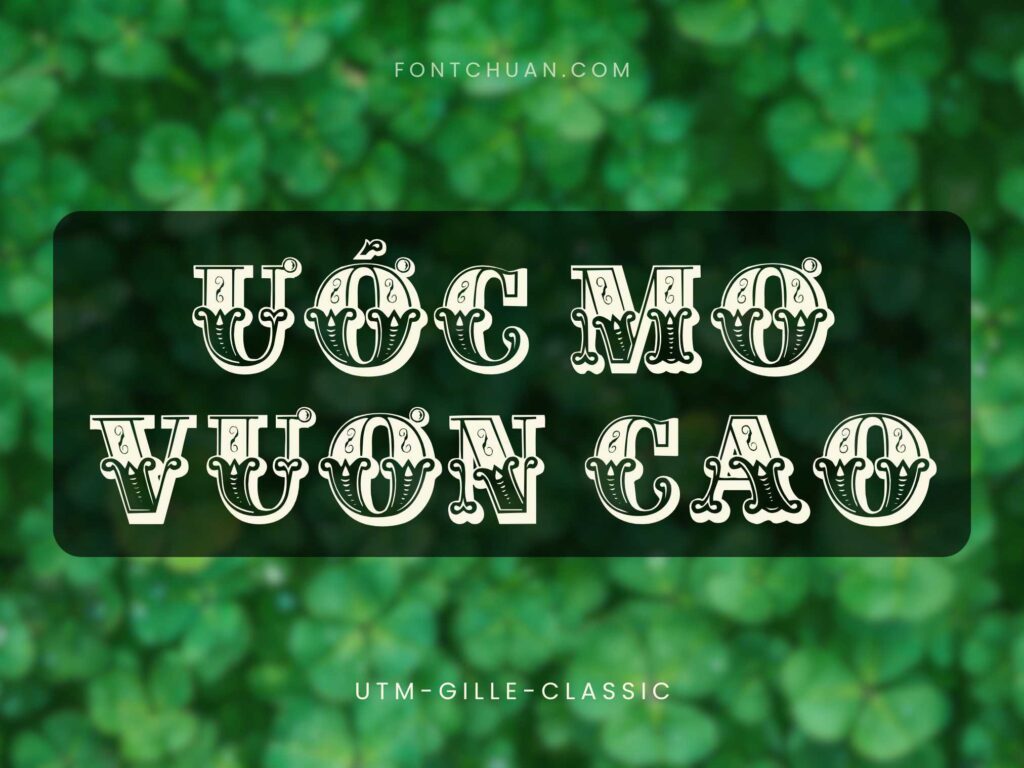
Font UTM Gille Classic Việt Hóa
Gille Classic là một font chữ thuộc thể loại fancy, ban đầu được phát triển bởi Joseph Gille vào năm 1820 và sau đó được Michael Hagemann tái thiết kế vào năm 2004. Font này mang đậm phong cách cổ điển với hơn 237 ký tự và 100 glyphs độc đáo, tạo nên sự hấp dẫn cho các thiết kế mang tính hoài cổ và nghệ thuật. Font đã được Việt hóa bởi Thiên Minh, hỗ trợ đầy đủ tiếng Việt cùng hơn 200 ngôn ngữ khác, giúp mở rộng khả năng sử dụng. Thành viên của Font Chuẩn đã sưu tầm và giới thiệu font này nhằm đáp ứng nhu cầu bạn đọc, cung cấp nguồn tham khảo chất lượng và ứng dụng thực tế vào các dự án thiết kế
Về đặc điểm thiết kế, Gille Classic sở hữu các nét chữ tinh tế, đường cong mềm mại và độ tương phản cao, tạo nên sự thanh lịch và cổ điển. Font này phù hợp cho các ứng dụng như thiết kế bìa sách, poster, thiệp mời, và các dự án nghệ thuật khác. Các ngành nghề như quảng cáo, ẩm thực, thiệp cưới và giáo dục có thể tận dụng font này để tạo nên sự khác biệt và thu hút trong các ấn phẩm thiết kế